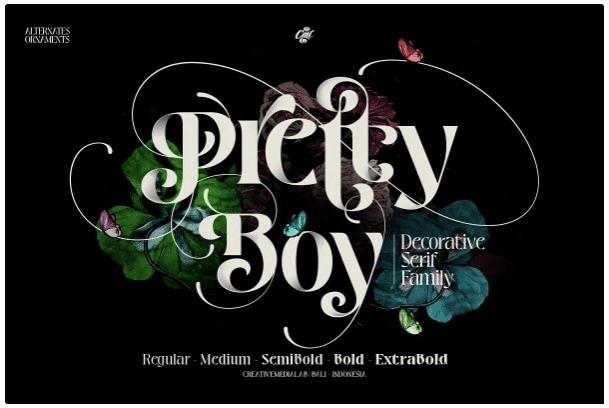
[Creativemarket] Pretty Boy Font (2021)
Представляем Pretty Boy - декоративное семейство шрифтов с засечками.
Этот шрифт состоит из пяти начертаний и орнамента. Он имеет множество альтернативных вариантов расположения, чтобы получить сказочное и очаровательное типографское искусство.
Орнамент Pretty Boy прекрасно сочетается с любыми шрифтами!
Этот декоративный шрифт с засечками идеально подходит для оформления фильмов, плакатов, свадебных приглашений, а также для логотипов, брендинга, заголовков и этикеток.